Bộ sưu tập font chữ Việt hóa đẹp mắt dành cho dân thiết kế sáng tạo
Font chữ đẹp là những kiểu chữ được đầu tư thiết kế tỉ mỉ, dễ đọc và linh hoạt ứng dụng. Khám phá ngay 10+ mẫu font đa phong cách từ đơn giản đến nghệ thuật, hoàn hảo cho dự án thiết kế, in ấn, thiệp mời hay quảng cáo của bạn.
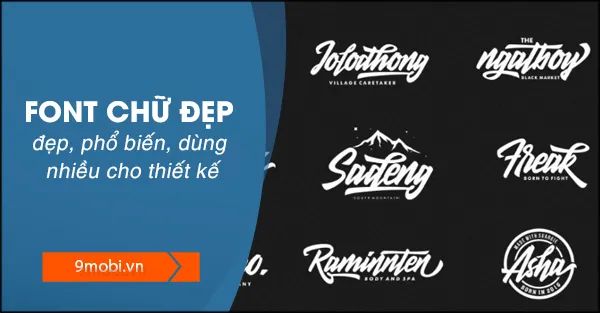
I. Bộ sưu tập font chữ ấn tượng nhất
1. Bộ sưu tập font chữ đẹp dành riêng cho Facebook
Là nền tảng mạng xã hội hàng đầu thế giới, Facebook không chỉ là nơi kết nối mà còn là không gian kinh doanh lý tưởng. Việc sử dụng font chữ độc đáo sẽ giúp bài đăng của bạn trở nên nổi bật và thu hút hơn bao giờ hết.
Bạn có thể dễ dàng thay đổi kiểu chữ Facebook sang in nghiêng, in đậm hay gạch ngang thông qua công cụ Yaytext. Tripi đã hướng dẫn chi tiết cách thực hiện trong bài viết trước đó.
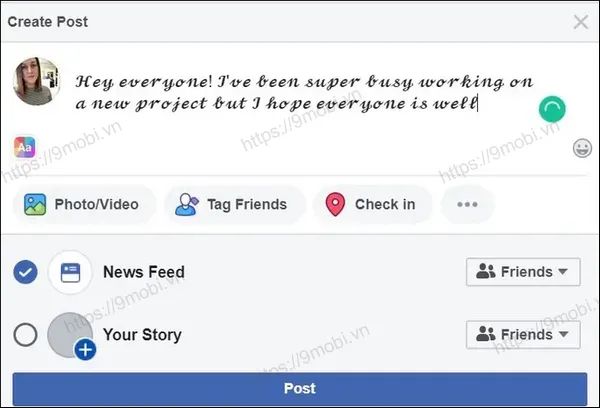
2. Tuyển tập font tiếng Việt đẹp mắt đã được Việt hóa
- Font Lato: Là font chữ sans-serif hiện đại với thiết kế thanh thoát, các đường nét mềm mại và hài hòa, mang lại vẻ đẹp tinh tế cho mọi thiết kế.
- Font iCielBC Downtown: Nổi bật với những đường nét góc cạnh, mạnh mẽ, hoàn hảo cho các thiết kế đồ họa đương đại và ứng dụng trang trí nghệ thuật.
- Font SVN-TheUntold Story: Mang phong cách độc bản, đầy cá tính, là lựa chọn lý tưởng cho những dự án sáng tạo đột phá.
3. Bộ sưu tập font chữ đẹp tối ưu cho Word và Excel
- Font Be Vietnam: Đa dạng phong cách từ mềm mại đến thanh lịch, được thiết kế chuyên biệt để tối ưu hiển thị tiếng Việt trong mọi văn bản.
- Font Roboto: Là kiểu chữ sans-serif hiện đại với các đường nét tròn trịa, cân đối, mang lại trải nghiệm đọc mượt mà và dễ chịu.
- Font Source Sans Pro: Sở hữu những đường cong mượt mà và đồng nhất, hoàn hảo cho các ấn phẩm in ấn chuyên nghiệp và thiết kế đồ họa tinh tế.
4. Tuyển tập font chữ đỉnh cao dành riêng cho thiết kế đồ họa
- Font Gardener: Mang phong cách phóng khoáng với nét chữ tự nhiên, kích thước biến hóa, lý tưởng cho các thiết kế nghệ thuật và chủ đề thiên nhiên.
- Font Typewriter: Tái hiện phong cách máy đánh chữ cổ điển với các ký tự đều tăm tắp và nét sắc sảo, phù hợp cho tài liệu kỹ thuật và văn bản mang hơi hướng retro.
- Font Global: Kiểu chữ tối giản nhưng vô cùng linh hoạt, dễ đọc trên mọi nền tảng từ in ấn đến kỹ thuật số.
- Font MORVA Typeface: Nét chữ sắc sảo với độ dày đồng nhất, tạo nên phong cách thiết kế tối giản nhưng vẫn đầy thu hút và ấn tượng.
5. Tuyển tập font chữ viết tay nghệ thuật và bảng chữ cái đẹp nhất
- Font Variane Script: Phong cách viết tay quý phái với những nét uốn lượn tinh xảo, mang đến vẻ đẹp sang trọng cho mọi thiết kế.
- Font Comfortaa: Kiểu chữ hiện đại với các góc bo tròn mềm mại, tạo cảm giác thân thiện và dễ đọc trong mọi ứng dụng.
- Font One day: Nét chữ cursive thanh lịch với đường cong duyên dáng, hoàn hảo cho thiệp mời và các ấn phẩm sang trọng.
- Font Fredoka: Nét chữ đậm rõ ràng và nổi bật, lý tưởng cho thiết kế đồ họa ấn tượng và các dự án sáng tạo đa phương tiện.
Bên cạnh các font chữ nghệ thuật, font chữ tiểu học (kiểu chữ tập viết có ô ly) được đông đảo giáo viên và phụ huynh tin dùng để rèn chữ đẹp cho học sinh từ lớp 1 đến lớp 5. Bộ sưu tập 19 mẫu chữ HP001 này sẽ giúp việc luyện chữ trở nên dễ dàng và hiệu quả hơn bao giờ hết.